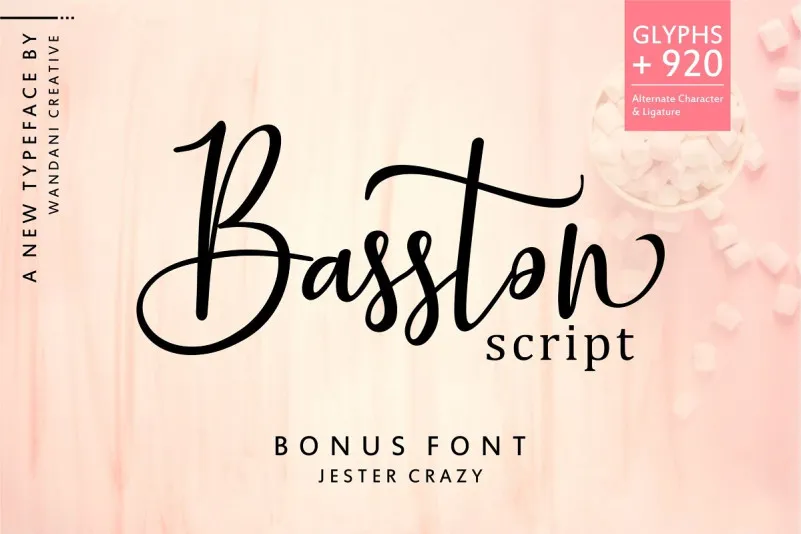
Basston Script Font Duo – Download Grátis
A Basston Script Font Duo é uma opção perfeita para designers que buscam um estilo elegante e encantador. Esta font script é ideal para criar designs de chamigrafia, projetos de marca ou embalagens distintivas. Como menciona o designer wandani.creative, esta fonte vem com mais de 920 alternativas e ligaturas, permitindo-lhe criar designs de chamigrafia impressionantes em um processo simples e rápido. Perfeita tanto para a criação de logotipos quanto para projetos de embalagens ou qualquer outro tipo de design, a Basston Script é uma escolha sólida que lhe dará aquele estímulo necessário para levar a sua marca ao próximo nível. Com seu estilo chamigrafia, a fonte mantém o equilíbrio elegante e encantador que se espera em um bom script. O download da Basston Script Font Duo é uma escolha certa para qualquer designer procurando por recursos gráficos de alta qualidade e versatilidade.